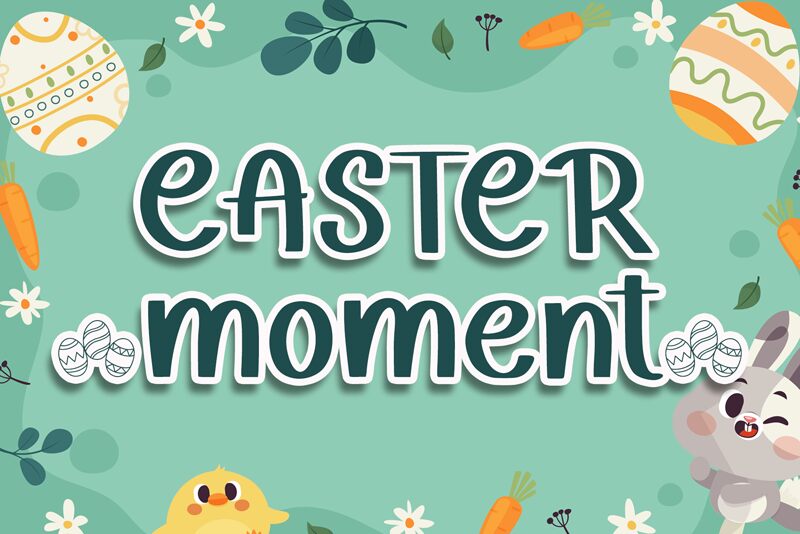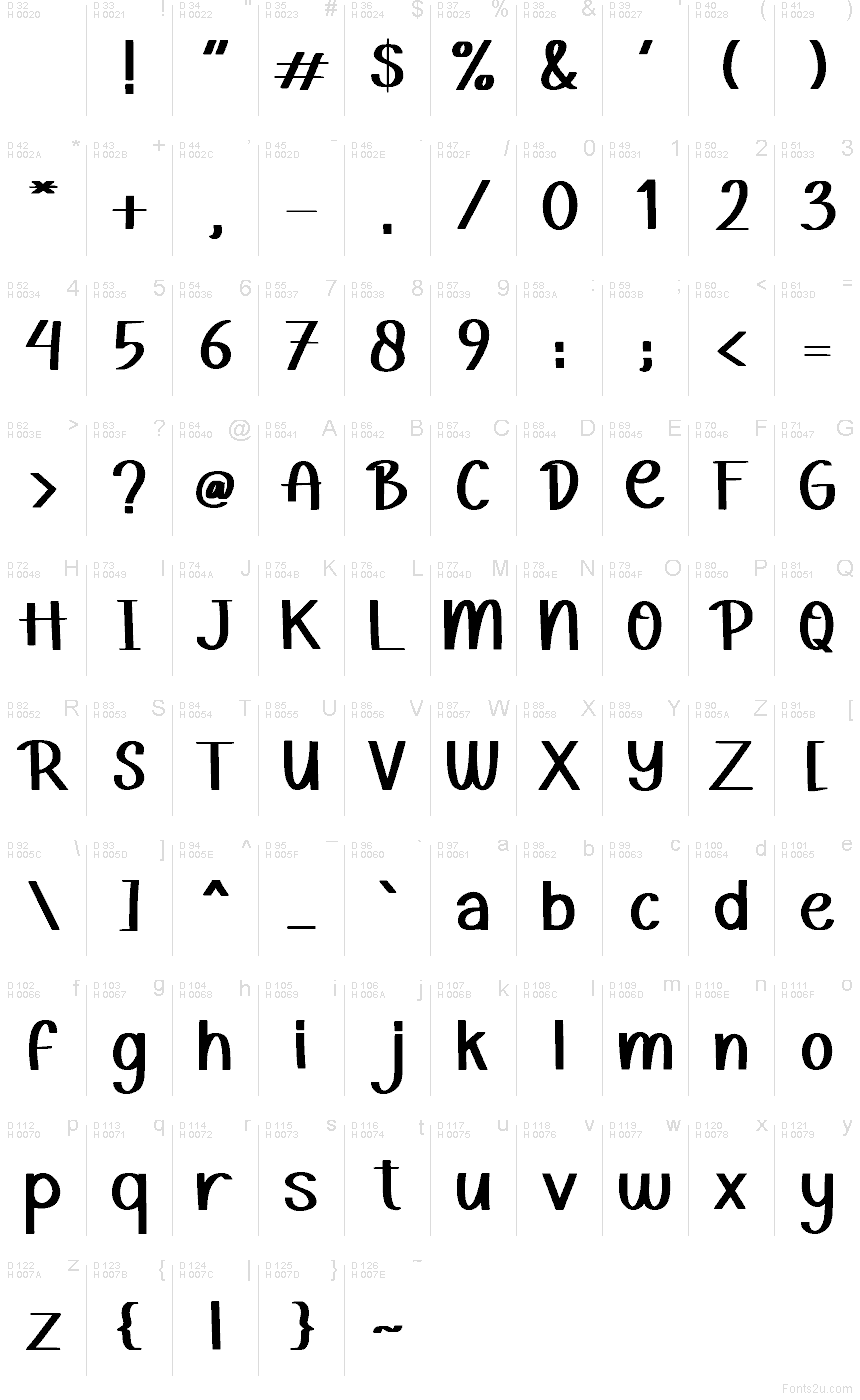
Easter Moment
Easter Moment od AEN Creative Studio je bezplatné písmo s rukopisným vzhľadom, ktoré tvoria široké, zaoblené siluety a mäkké zakončenia, vďaka čomu pôsobí pokojne a vyvážene. Jeho rytmus je jemne formálny, s plynulými krivkami a mierne rozšírenými ťahmi, ktoré dodávajú tomuto fontu kompozíciu vhodnú aj na tlač.
Vďaka tejto harmónii je prirodzenou voľbou pre jarné pohľadnice, darčekové štítky, obaly na pečivo, nadpisy pozvánok a citáty na sociálne siete, kde hľadáte rukopisný štýl s dávkou elegancie. Zaoblené tvary sa hodia aj na logá butikov a etikety produktov, najmä ak hľadáte niečo osobné bez rozháranosti bežných písiem písaných fixkou.